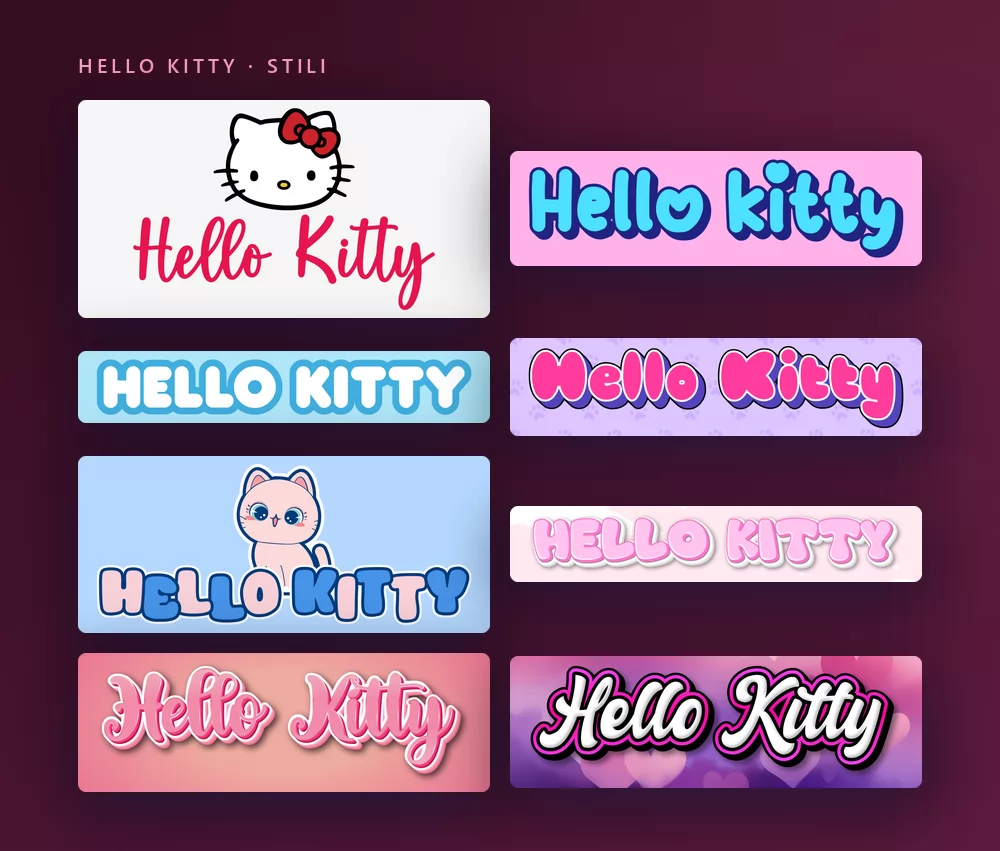
Vengono tutti dallo stesso generatore di font Hello Kitty, con uno stile diverso scelto dalla lista. Niente da installare, nessun account.
Informazioni sul font di Hello Kitty
Hello Kitty è un personaggio giapponese creato nel 1974 per Sanrio dalla designer Yuko Shimizu, e disegnato dal 1980 da Yuko Yamaguchi. Una gatta bianca con un fiocco rosso sull'orecchio sinistro e senza bocca visibile, apparsa per la prima volta su un portamonete di vinile nel 1975 e diventata uno dei personaggi più concessi in licenza al mondo, su giocattoli, cartoleria, abbigliamento e praticamente tutto il resto.
Il logo ha usato diversi lettering nel corso degli anni, e nessuno è stato pubblicato come carattere: sono lettering su misura, disegnati per Sanrio. Per questo "il font di Hello Kitty" non vuol dire la stessa cosa per tutti, e per questo i siti di font elencano dei simili invece di una risposta sola. I nomi che compaiono in ogni lista sono Janda Happy Day, Boldins, Odin Rounded, Jam Sessions, Hello Heartache e LMS Hello Kitty Hello.
Una cosa da sapere prima di scaricare qualsiasi cosa: il font "Hello Kitty" più scaricato, quello di Woodcutter su DaFont con un milione e mezzo di download, è un font di dingbat. Ogni tasto scrive un disegnino di Kitty, non una lettera. Adorabile, ma un nome non lo scriverà.
Come creare un testo Hello Kitty
Passo 1. Scrivi il nome
Apri il generatore e sostituisci il testo di esempio con il tuo: il nome di un bambino, "Buon compleanno", una parola per uno sfondo del telefono. Le lettere si ridisegnano mentre scrivi, sotto il muso di Kitty. Tienilo in minuscolo con l'iniziale maiuscola: lo stile del logo è un corsivo, e una parola in maiuscolo perde le legature che la fanno leggere come scritta a mano.
Passo 2. Scegli uno stile
Il classico è il corsivo rosso sotto il muso bianco su uno sfondo grigio chiaro. La scheda Stili permette di cambiare separatamente riempimento, contorno e ombra, così tieni la forma delle lettere e porti i colori altrove: un rosa tenue, un azzurro pastello per una festa Cinnamoroll, bianco sui cuori.
Passo 3. Scegli il formato
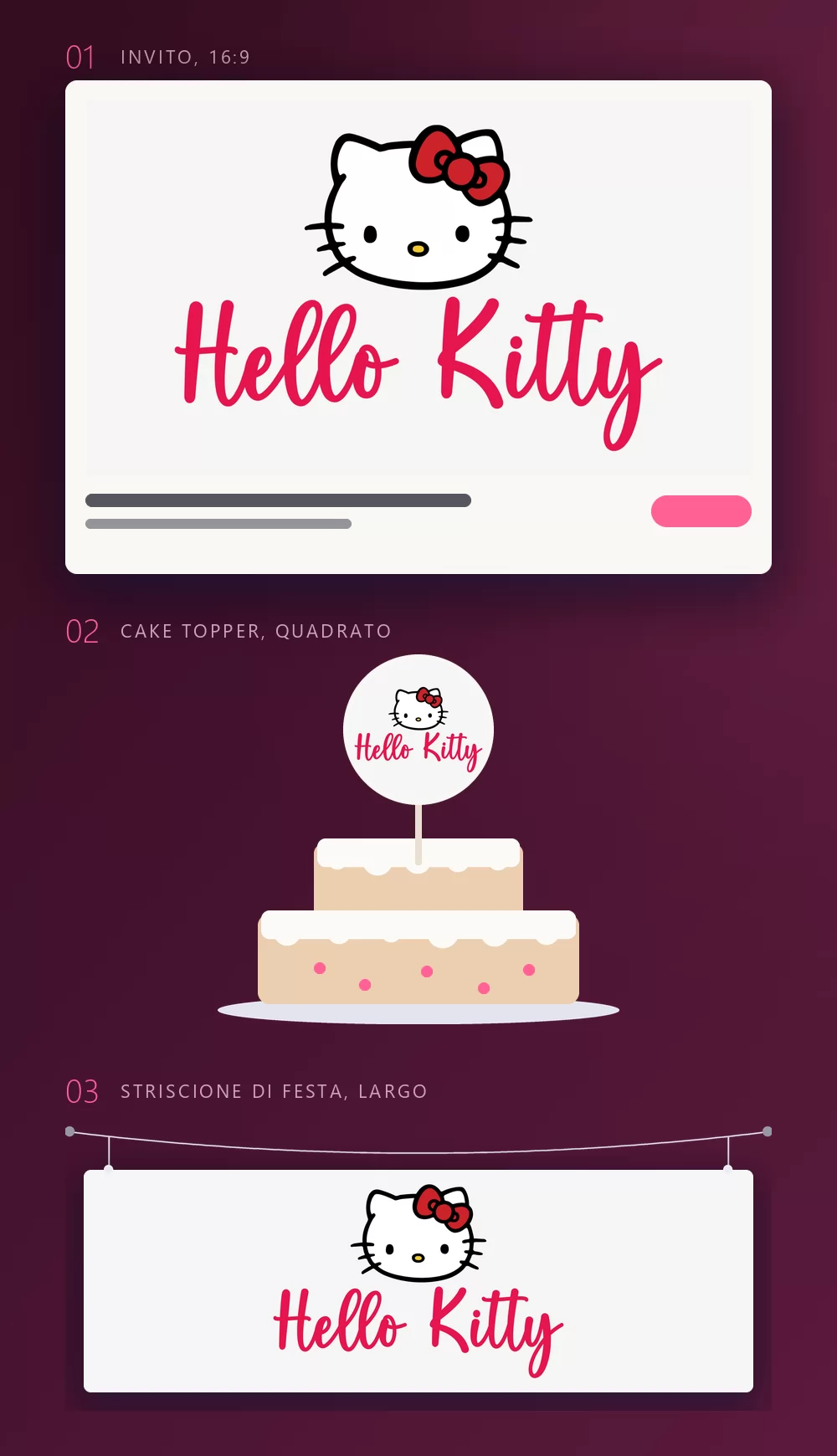
Imposta il formato prima di esportare e dopo non dovrai ritagliare niente. Un 16:9 per un invito, un quadrato per un cake topper o un adesivo, una striscia larga per uno striscione lungo la parete. Le tre simulazioni qui sopra sono ciò che diventano quei formati una volta stampati.
Passo 4. Scaricalo
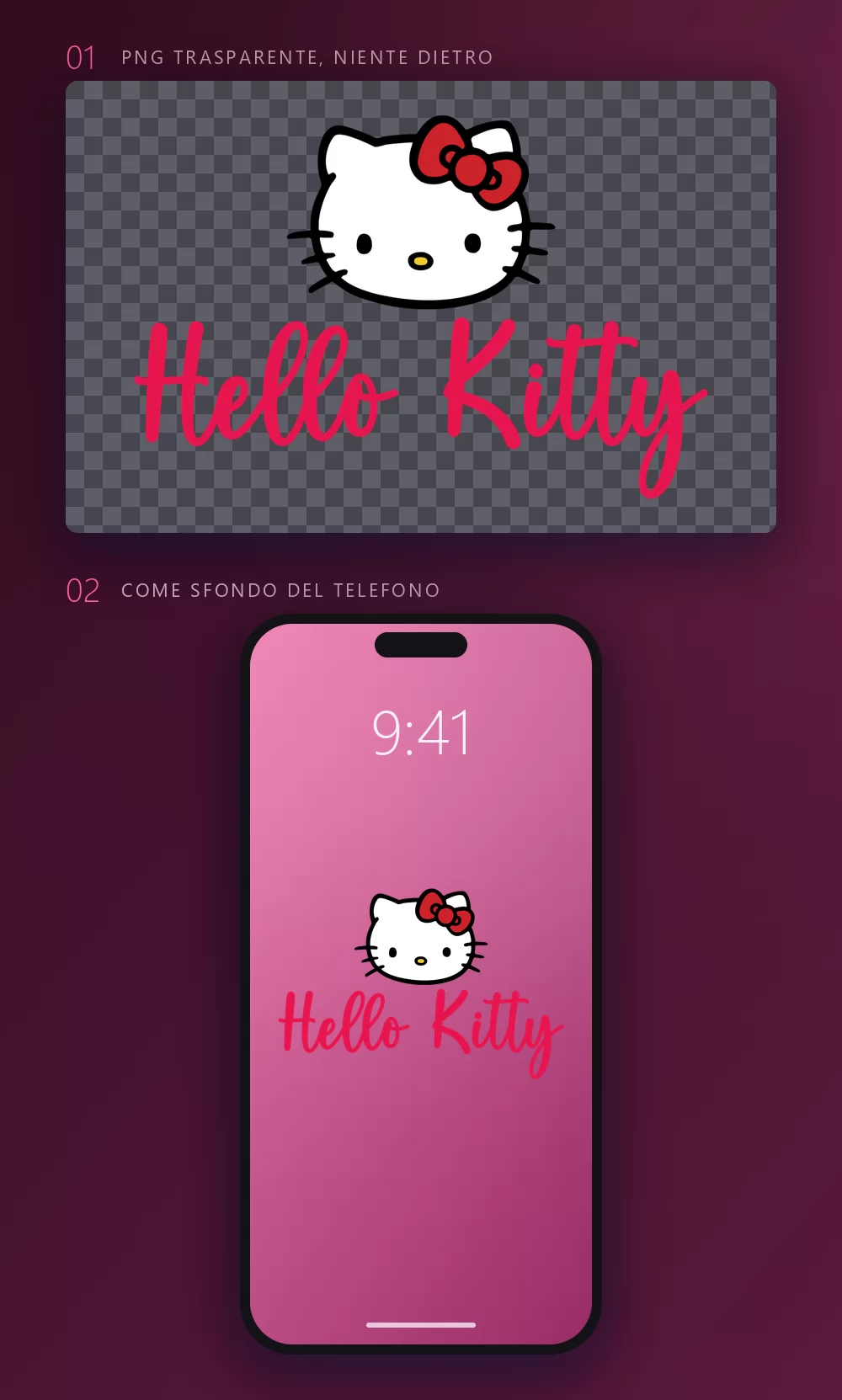
Nella scheda Scarica, prendi il PNG trasparente se vuoi mettere il nome sul tuo progetto. È l'opzione che quasi tutti si perdono, ed è quella che conta per uno sfondo, un adesivo o uno stampabile: il tuo sfondo, Kitty e il nome sopra, nessun riquadro grigio intorno.
I nomi lunghi riempiono subito la larghezza
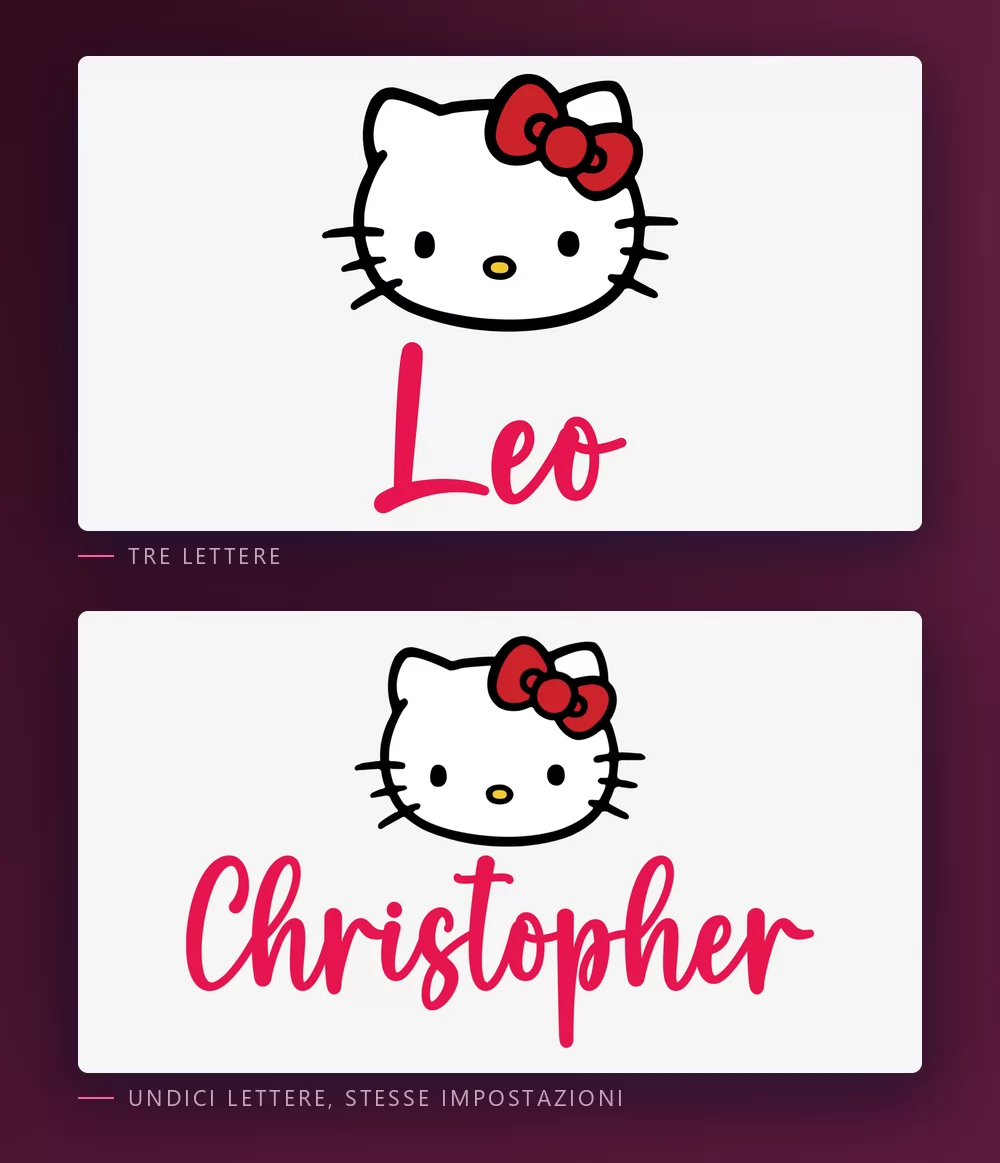
Più lettere ci sono, più si stringono. La spaziatura dei caratteri è un cursore della scheda Testo: aprila un po' e un nome lungo smette di sembrare schiacciato. La stessa scheda ha zoom, interlinea, curva e rotazione.
Lo stile Hello Kitty o lo stile kawaii
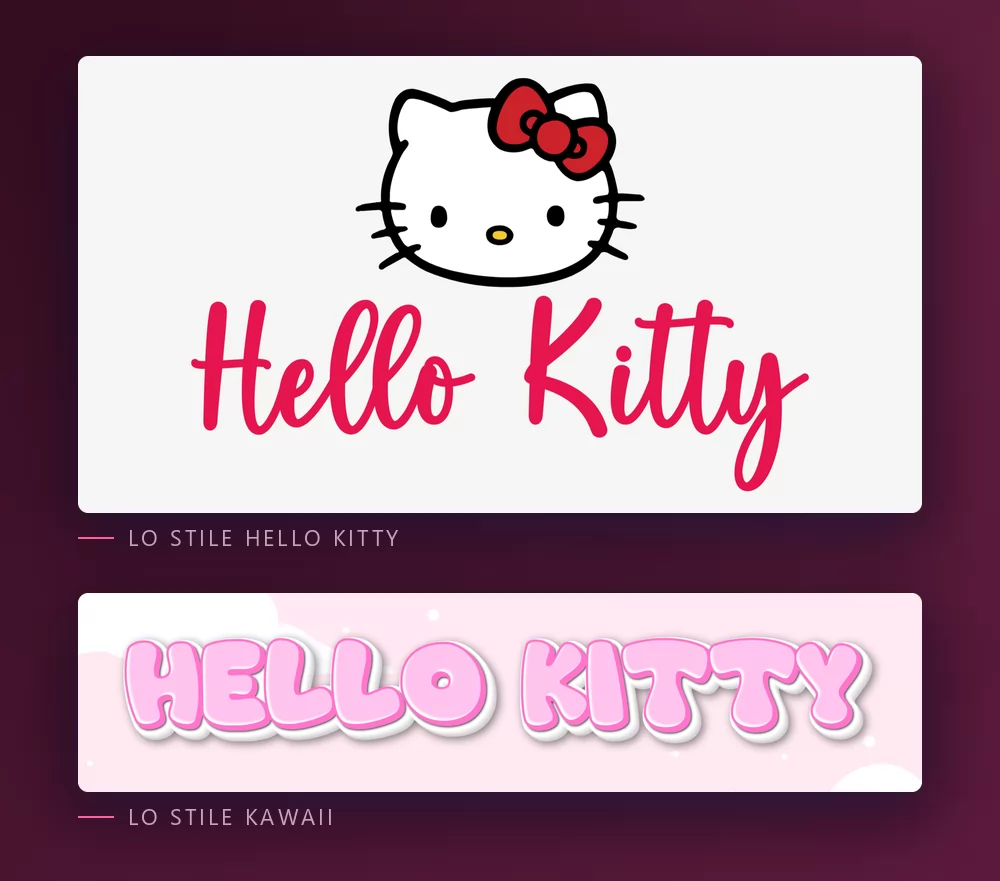
Lo stile Hello Kitty è il logo stesso: il muso bianco con il fiocco rosso e il nome in un corsivo rosso sotto. È quello che quasi tutti hanno in mente, ed è quello giusto per tutto ciò che deve dire Hello Kitty a colpo d'occhio.
Lo stile kawaii sono lettere a bolla rosa su nuvole pastello, senza nessun personaggio. Non porta niente del marchio Sanrio, e questo lo rende la scelta migliore per un'agenda, un'insegna di negozio o uno sfondo del telefono che vuole solo essere carino. Il generatore di testo kawaii lo ha tra le impostazioni.
Quale font, se vuoi installarne uno
Il logo in sé non è un font. È un lettering su misura disegnato per Sanrio, quindi qualsiasi file chiamato "font Hello Kitty" è la ricostruzione di qualcuno, o un font che per caso gli somiglia.
Janda Happy Day, di Kimberly Geswein, è quello che quasi tutte le liste mettono per primo: una scrittura a mano tonda e saltellante che si legge come il logo. Su DaFont è indicato come gratuito per uso personale, con più di ottocentomila download.
Odin Rounded è il gratuito con la licenza pulita: un sans tondo semplice indicato come gratuito al 100 % su DaFont, oltre mezzo milione di download. Dà la sensazione morbida e tonda del marchio senza il rimbalzo.
Boldins è un altro corsivo per uso personale che compare, e LMS Hello Kitty Hello, su FontSpace dal 2001 con più di un milione di download, è freeware solo per uso non commerciale. Leggi il readme prima che uno di questi finisca su qualcosa che vendi.
Per lavori con clienti, dove la licenza deve essere pulita, le opzioni oneste sono i font tondi a licenza aperta di Google Fonts: Comfortaa, un tondo geometrico che è il più vicino al marchio, e Fredoka, più saltellante, con un'intera gamma di pesi. Nessuno dei due è un font di Hello Kitty. Entrambi danno l'aspetto morbido e tondo con una licenza che nessuno può contestare, ed entrambi sono disponibili dentro Canva.
Perché il mio testo sembra sbagliato accanto al logo vero? Di solito è il muso che manca, non il font. Il corsivo rosso da solo è solo un corsivo rosso. Con il muso bianco e il fiocco rosso sopra, si legge come Hello Kitty anche in un altro font.